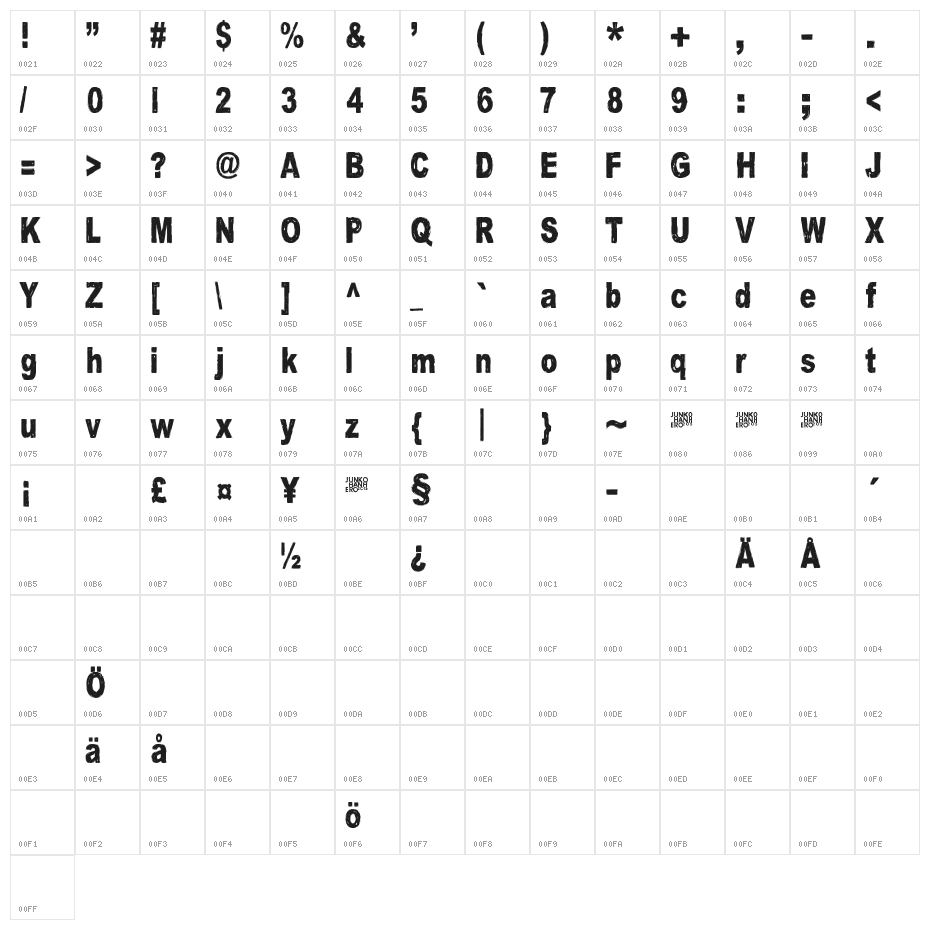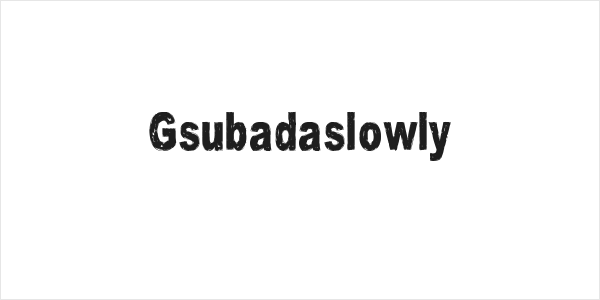
Gsubadaslowly Font
✎ Distorted Eroded
| Kategorien | Distorted Eroded |
| Gesamtstil | Vintage, Grunge |
| Vorgeschlagene Projekte | Ideal for posters, album covers, branding for edgy products, and any design requiring a bold, vintage aesthetic. |